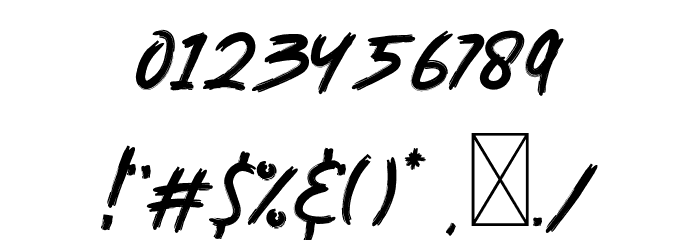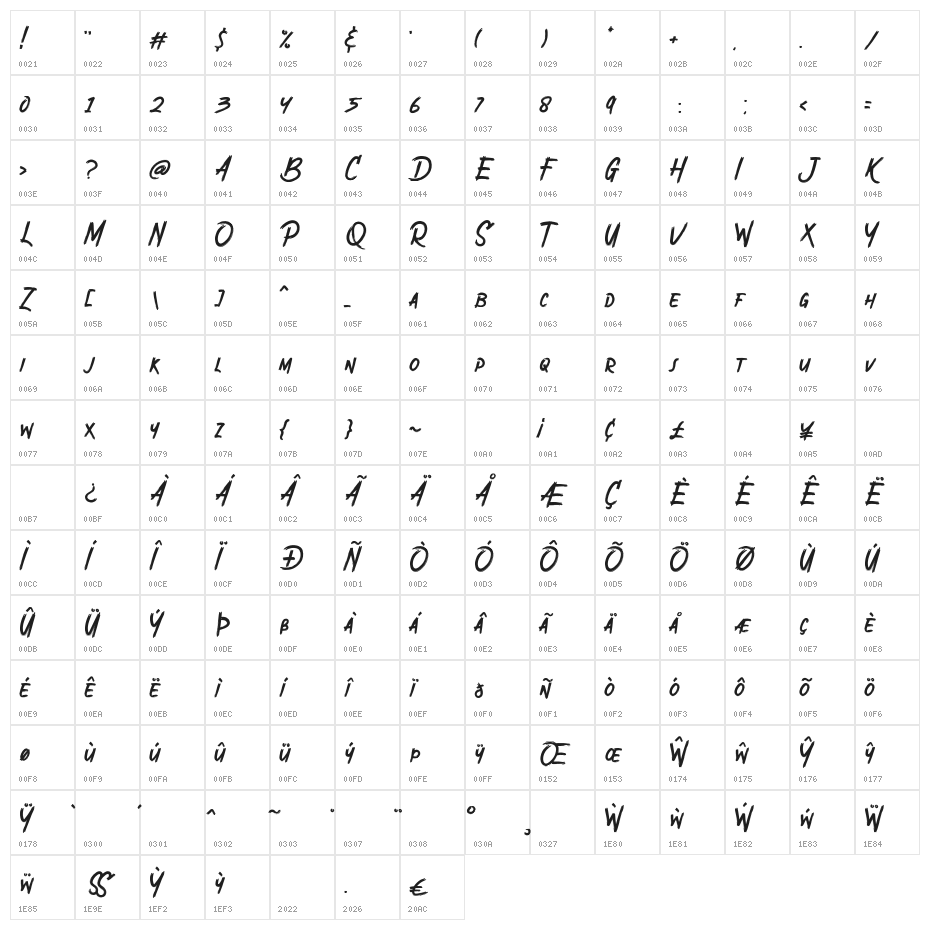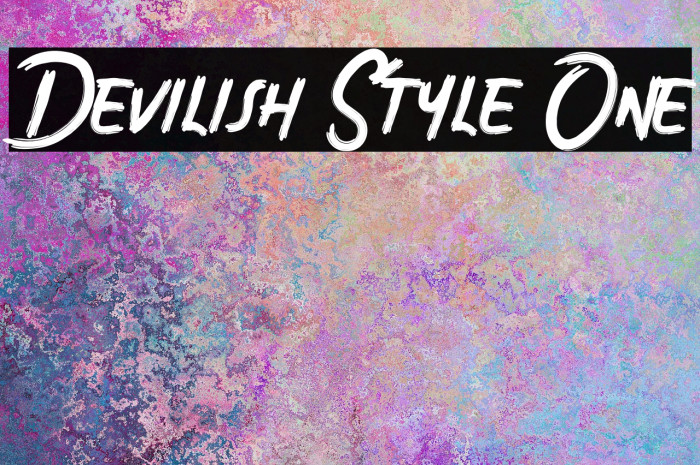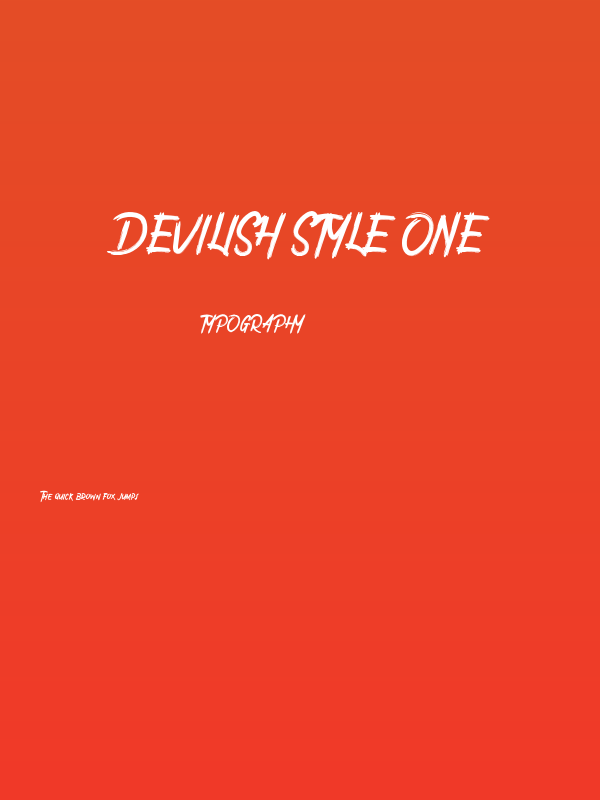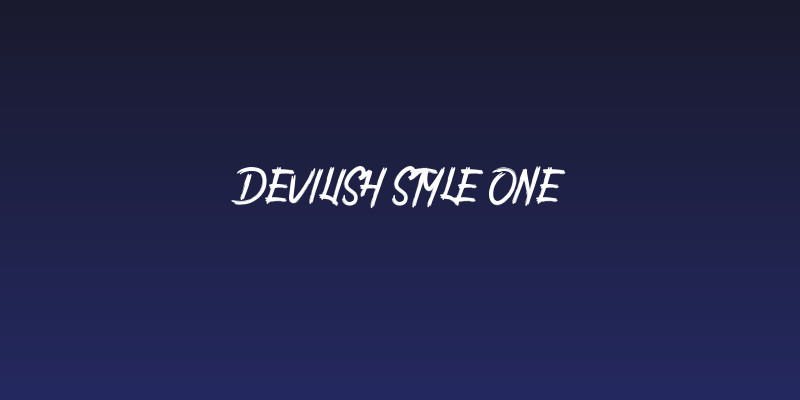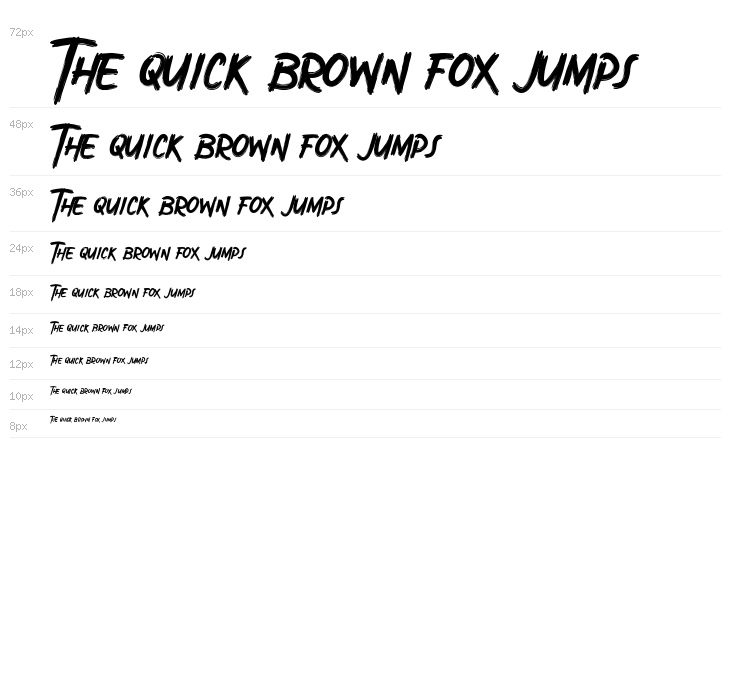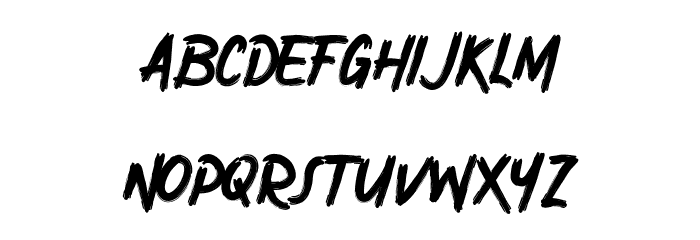
Devilish Style One Font
| Estilo general | Modern, Edgy |
| Proyectos propuestos | Ideal for music album covers, extreme sports branding, edgy fashion labels, and dynamic poster designs. |